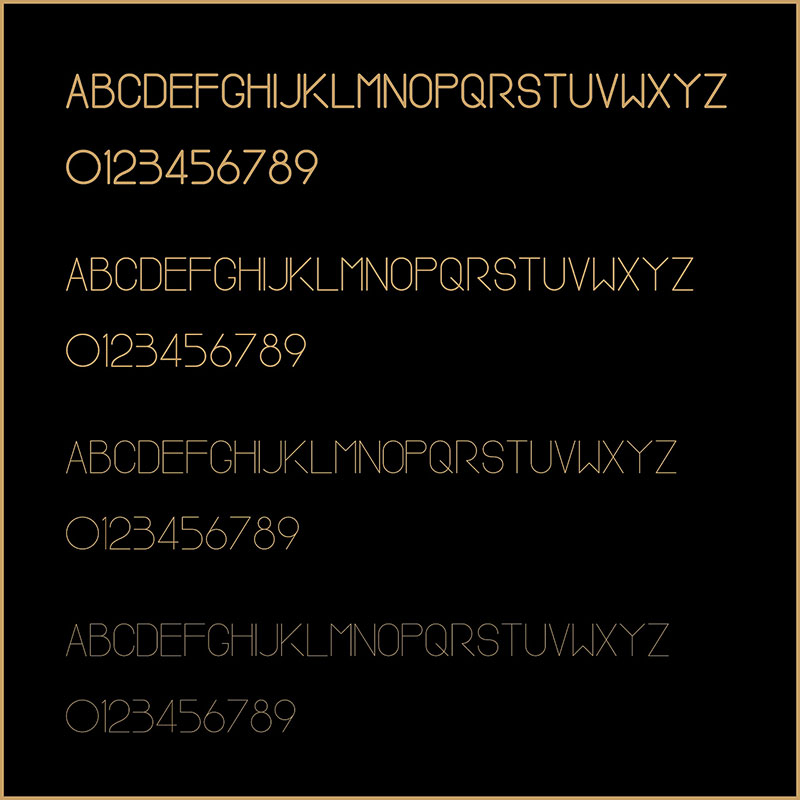
这里有26(或许×2\(^o^)/)个字母,我们想要设计一款英文字体来自用,于是经过拆解与重构,根据需求与法则,分别做出来这样26个大、小写字母,现在放上来与大家共同探讨学习下,大家都可以免费下载来使用哦。
原本只打算做26个大写,后来发现有软件可以制作成字体安装包,于是又做出了小写和数字,但是由于做成字体安装包比较不顺利(刚开始还以为自己学会了新的技能,后来发现想多了),所以我们就一直放着,然后得空就拿出来用PC和MAC不同的字体制作软件来优化下,而导出总是会出现各种问题,就废了差不多2个月才拿出来见人,当然现在还是有问题,但是太费时间,所以暂时就先不调整了,一般使用或是作为标题使用还是不错的。